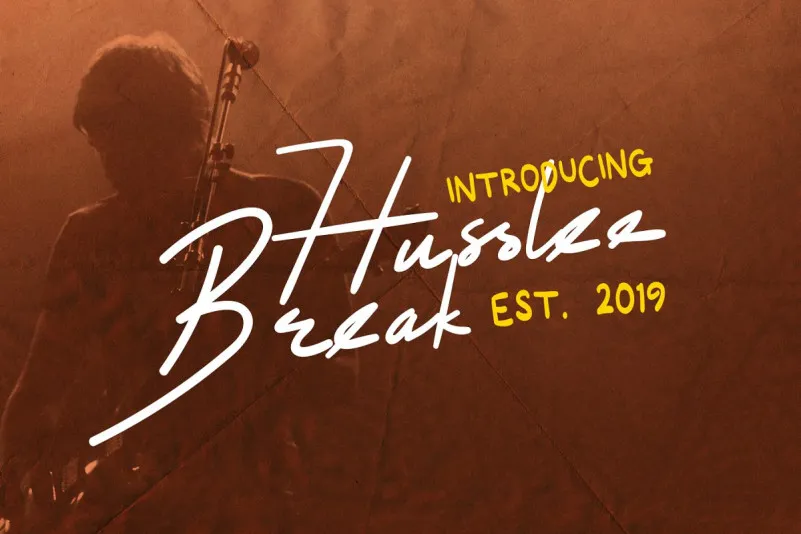
Husslee Break Script Font – Fonte Grátis
Husslee Break Script Font
Esta fonte ‘Husslee Break Script Font’ é perfeita para quem busca uma escrita manuscrita natural e elegante. Desenvolvida pelo designer 178-MC, essa fonte tem um toque de frescor e limpeza que mantém o charme da escrita manual. Seu estilo retrô e clean combina muito bem com as mais variadas aplicações gráficas, desde design de roupas até criação de cartões de visita ou assinaturas para blogs e redes sociais. Husslee Break é uma opção perfeita para quem deseja dar um toque único em seus projetos. Suas alternativas oferecem flexibilidade, permitindo que você personalize a impressão da fonte ao seu gosto. Seja para carregar sua estética de moda com personalidade ou para adicionar um toque sofisticado a sua newsletter de blog, esse é o tipo de font que fará uma diferença. Seja qual for a aplicação que você escolher, certifique-se de que Husslee Break Script estará sempre ao seu lado. Seu charme natural e elegante permite que você personalize seus projetos de forma única e profissional.